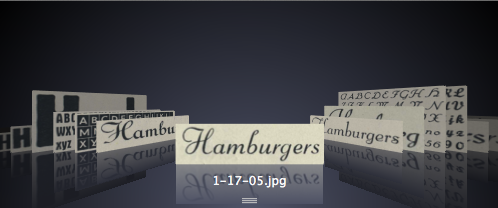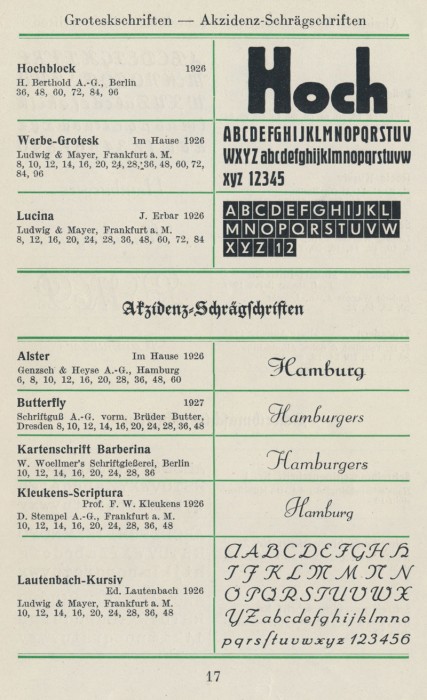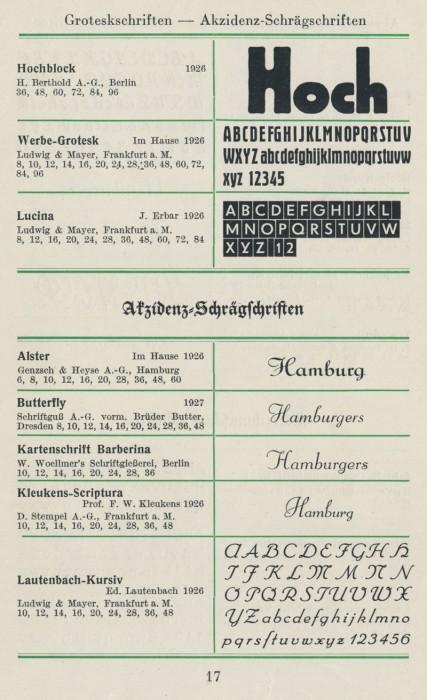
Wagner Script aka Troubadour.
This gem of a script was what metal era typographers called a “continental face”, which essentially meant an old, most likely uncredited, metal face that was common to many European foundries. This particular one ran the rounds in the first half of the twentieth century under the names Donatello, Aigrette, Troubadour, Hertha, Butterfly and Gracia. A little research reveals its true origin to be circa 1926 at the Wagner & Schmidt foundry in Leipzig, where it was a bold script named Troubadour. A cut that was much lighter, more elegant, and much more suitable for larger display applications was made by the Amsterdam Lettergieterij in the late 1930s, under the name Gracia. Gracia was a common sight on perfume bottles, wine labels, chocolate boxes, and book covers in Europe for about four decades. Like many treasures of its kind, it seems to have never been considered for digital retooling until now.
Wagner Script corrects and greatly expands on the original metal concept, to include plenty of alternate forms, even as many as four variations on some characters. It also comes with extended range Latin-based language support. The Wagner Script package contains both Wagner Script Pro, a premium feature-loaded OpenType font for advanced typography applications, as well as three TTF fonts for the legacy format user.
Hier die ganze Seite – und die Info, dass es sich hierbei nicht um ein Schriftmuster handelt, sondern den Seemann, wie auch sonst. Es geht also um die fünfte Schrift von oben aus dem 1. Nachtrag, Seite 17.
Demnach handelt es sich um die Butterfly der Schriftguß A.-G., die 1927 in Dresden erschienen ist. myfonts kennt sie ebenfalls, sie hat also den Sprung ins digitale Zeitalter schon geschafft.